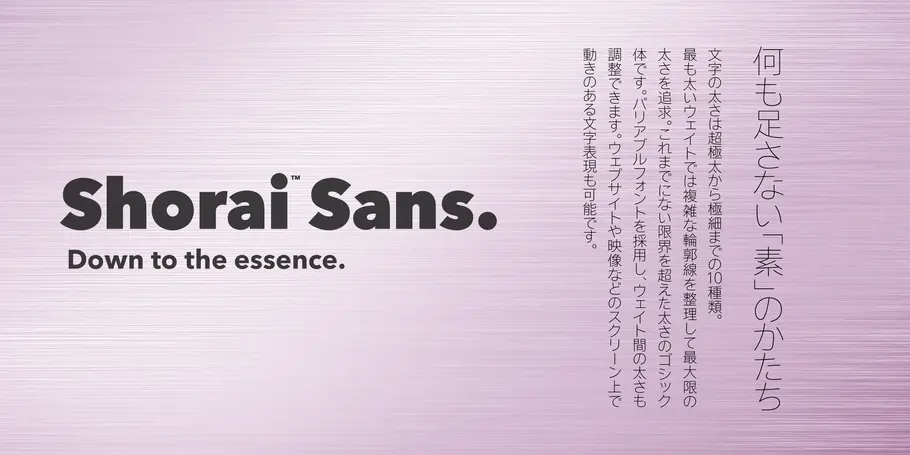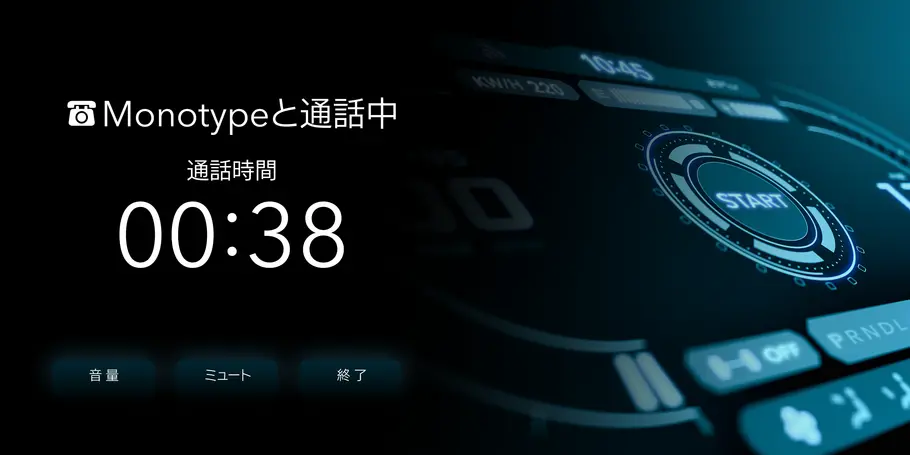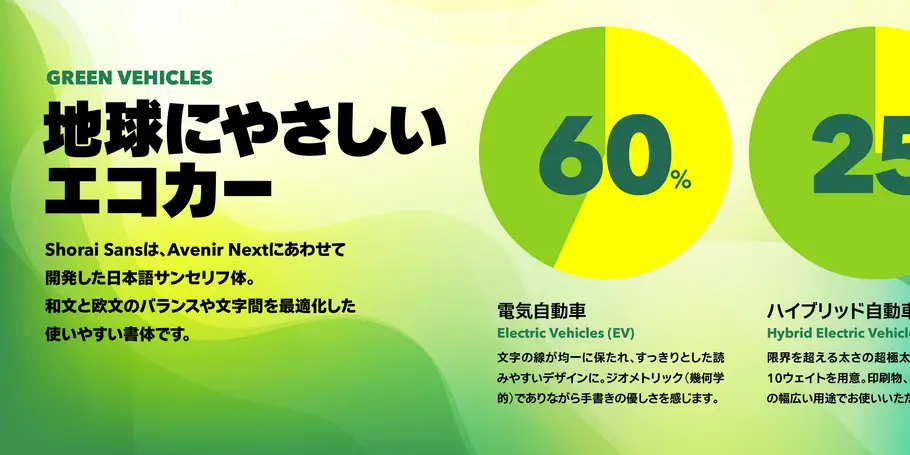
Shorai™ Sans
何も足さない「素」のかたち
Shorai™ Sansは、Avenir® Nextの造形的要素を取り入れてデザインされたジオメトリック・サンセリフ体で、たづがね®角ゴシックに続くMonotypeの日本語書体です。
Avenir Nextの幾何学的な特徴を活かし、文字の線を均一に保ちました。骨格を極限まで単純化し、すっきりとした形にまとめています。
Shorai SansTMは、幾何学的な形状が特徴のMonotypeの日本語書体です。Avenir® Nextの造形的要素を取り入れてデザインされ、付属欧文には、和文にあわせて大きさや位置を調整したAvenir Nextを採用。和欧混植に最適化され、Shorai Sans単体で美しく読みやすいテキストを組むことができます。
文字の線をできるだけ整理し、骨格を極限まで単純化。線を均一に保つことで、すっきりと読みやすい明快な形を目指しました。シンプルで見やすい文字は、印刷物のほか、スマートフォンやタブレット端末などのデジタルデバイス、建物や標識のサインまで、幅広いニーズに対応しています。
文字の太さは超極太から極細までの 10 種類。最も太いウェイトの Heavy では、複雑な輪郭線を整理し、Monotype初の超極太の和書体を実現しました。
通常の単体ウェイトに加えてバリアブルフォントを採用しウェイト間の太さも調整できます。ウェブサイトや映像などのスクリーン上で動きのある文字表現も可能です。
2001年に独Linotype社(2013年に社名をMonotypeに変更)のタイプディレクターに就任。現在ドイツ在住。書体の品質管理のほか、自身のオリジナル書体の制作、有名な書体デザイナーであるヘルマン・ツァップ氏やアドリアン・フルティガー氏と共同での書体開発、過去の書体ファミリーの改刻、企業制定書体(コーポレートフォント)の開発を担当している。欧米、アジアを中心に講演やフォントデザインワークショップを行っているほか、世界的なタイプフェイスデザインコンテストの審査員も務めている。
東京藝術大学デザイン科を卒業後、英国レディング大学書体デザインコースで修士号を取得。2015年よりタイプデザイナーとしてMonotypeに在籍し、企業制定書体の開発や、書体選定をはじめとしたコンサルティングを行う。また、たづがね角ゴシックの制作メンバーとして、ファミリー展開やCJK(中日韓)言語に対応した字種拡張にも携わる。最近では、大学での講義や国際カンファレンスでの登壇を通じ、国内外に向けて書体についての発信をしている。
1958年から看板業3社に勤め、その後テレビ放送局でテロップ制作。デザインスタジオでフィニッシュ原稿作成。1968年フリーランスで広告版下制作。トヨタ乗用車マニアルイラスト制作。1970年石井タイプフェイスコンテスト1位を機に、2000年まで株式会社写研の写植機用書体20種制作。代表作にナールL、D、ゴナUがある。2000年から中村書体室設置、フォント開発を行う。2019年、中村ロゴシ74、ロゴゴ94をリリース。2018年からShorai Sans開発プロジェクトに参加する。